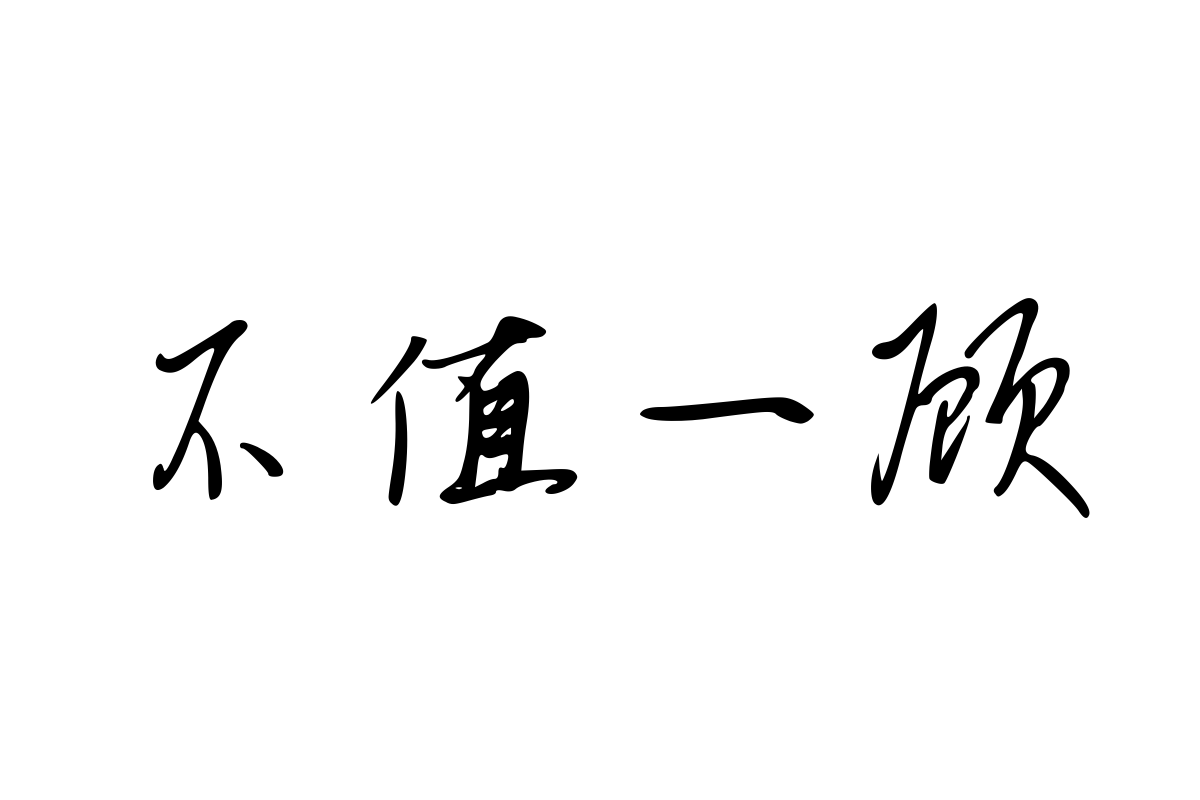
思雨聪聪草书体是一种独特的书法字体,以其独特的风格和魅力而闻名。这种字体的特点是笔锋流畅,线条粗犷有力,给人一种豪放不羁的感觉。它的笔画粗细变化丰富,既有尖锐的锋芒,又有柔和的韵味,使得整个字显得生动活泼。
思雨聪聪草书体的字形结构紧凑,但不失灵动。它既有传统的楷书严谨,又有草书的奔放,使得整体效果既有力度又不失美感。这种字体适合用于各种场合,无论是书写还是印刷,都能展现出其独特的魅力。
总的来说,思雨聪聪草书体是一种充满个性和创造力的字体,它以独特的风格和魅力吸引了众多书法爱好者的关注。